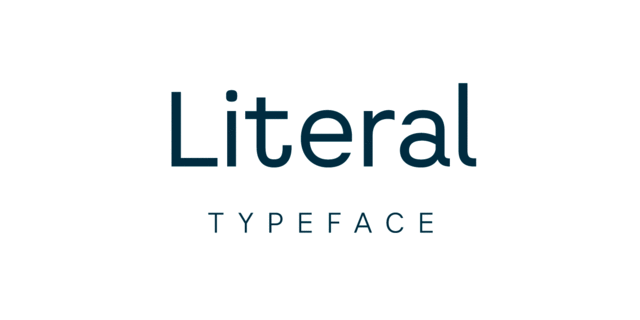
Literal – это современный гротеск с закрытыми формами. У шрифта 3 начертания: Light, Regular, Bold. Он поддерживает расширенную латиницу и кириллицу, в том числе азиатскую. Шрифт разработал Игорь Косинский в 2019 году.
Ассоциации c начертанием Literal BoldКачества и характер:
деловой, серьезный, стабильный, статичный, устойчивый, инженерный, точный, логичный, ровный, городской, качественный, западный, спокойный, современный, техничный, уверенный, надежный, спортивный, важный, убедительный, мужественный, мощный, сильный, авторитетный, заметный, тяжелый, индустриальный, техногенный, гладкий, крутой, футуристичный, автоматический